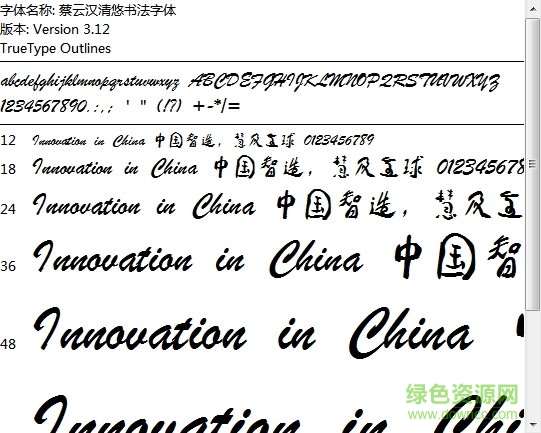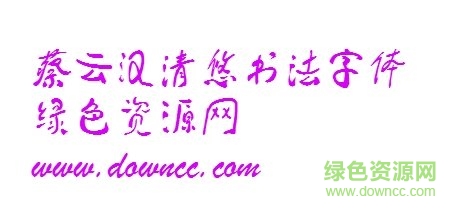
蔡云漢清悠書法字體是一款書寫流暢、造型獨特的毛筆書法字體,字跡連貫而不繚亂,張揚(yáng)灑脫飄逸之風(fēng),給人極佳的視覺美感,讓你的文字更具個性魅力,快來綠色資源網(wǎng)試試吧!
清悠書法字體擁有不一樣的書法風(fēng)格特色,造型上大氣而其實磅礴,給人清晰醒目的視覺呈現(xiàn),可以廣泛運用于平面設(shè)計、藝術(shù)設(shè)計等方面!